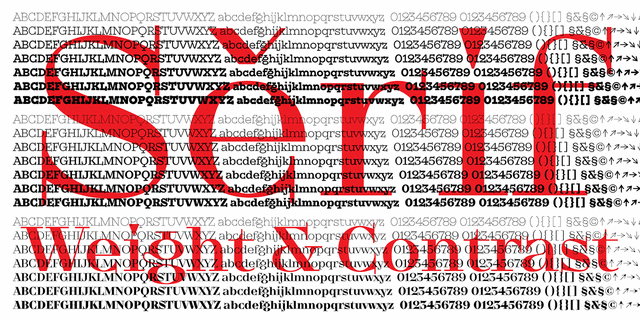
Брусковая часть супергарнитуры для Киева. Шрифт для Киева со многими лицами и крутым нравом появился тогда, когда к проекту #newkyivlogo (каштановый лист как логотип Киева) присоединился Дмитрий Растворцев. «Киев разный. Немного грубый. Немного интеллигентный. Немного тусовочный. Немного хипстерский. Немного традиционный. Это эклектичное город. Он легко включает разное и разных – это создает тот Киев, который я люблю. Шрифт такой же – немного грубый, немного интеллигентный, немного тусовочный, немного традиционный, немного дикий. И очень-очень разный.» – так описывает проект Александр Трегуб – основатель Projector и идейный вдохновитель нового логотипа Киева.
Ассоциации c семейством Kyiv Type SerifКачества и характер:
ироничный, устойчивый, винтажный, ровный, острый, современный, эстетский, твердый, оригинальный, характерный, модный, замысловатый, резкий, претенциозный, экстравагантный, нонконформистский, богемный, крафтовый, точный, убедительный, стабильный, четкий, статичный, консервативный, традиционный, мастерский, старомодный, ностальгический, добротный, олдскульный, прочный, надежный, серьезный, интересный, качественный, городской, ясный, культурный, выразительный, уверенный, странный